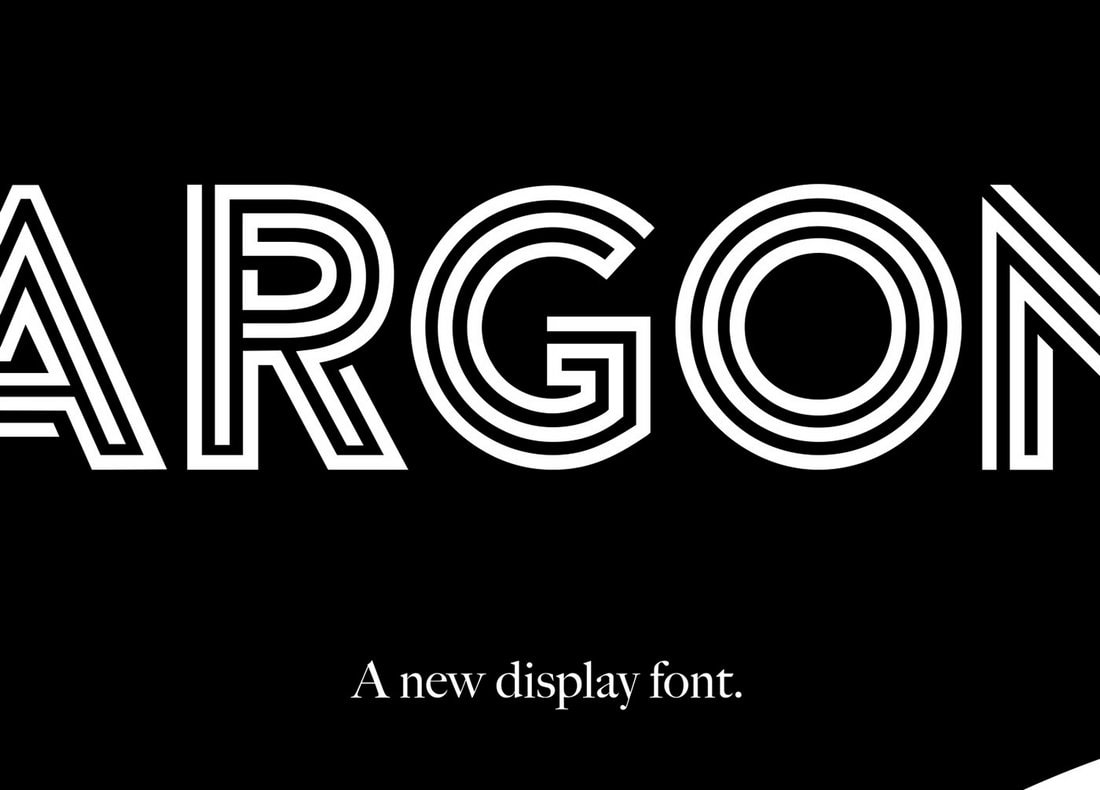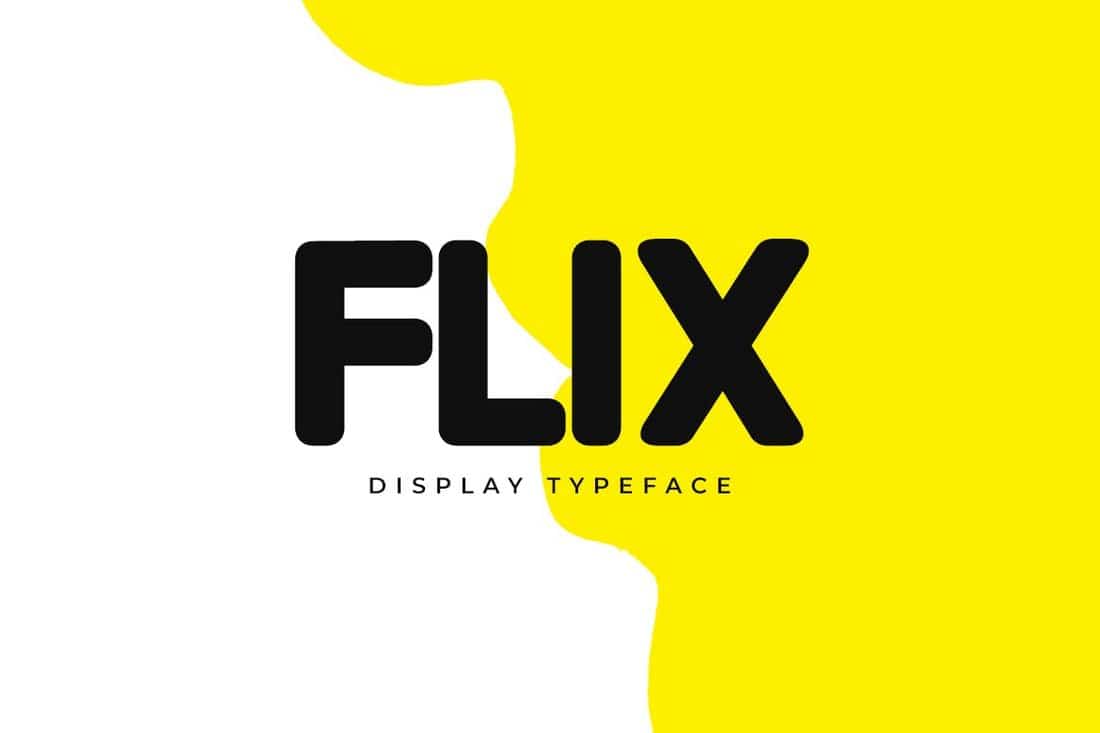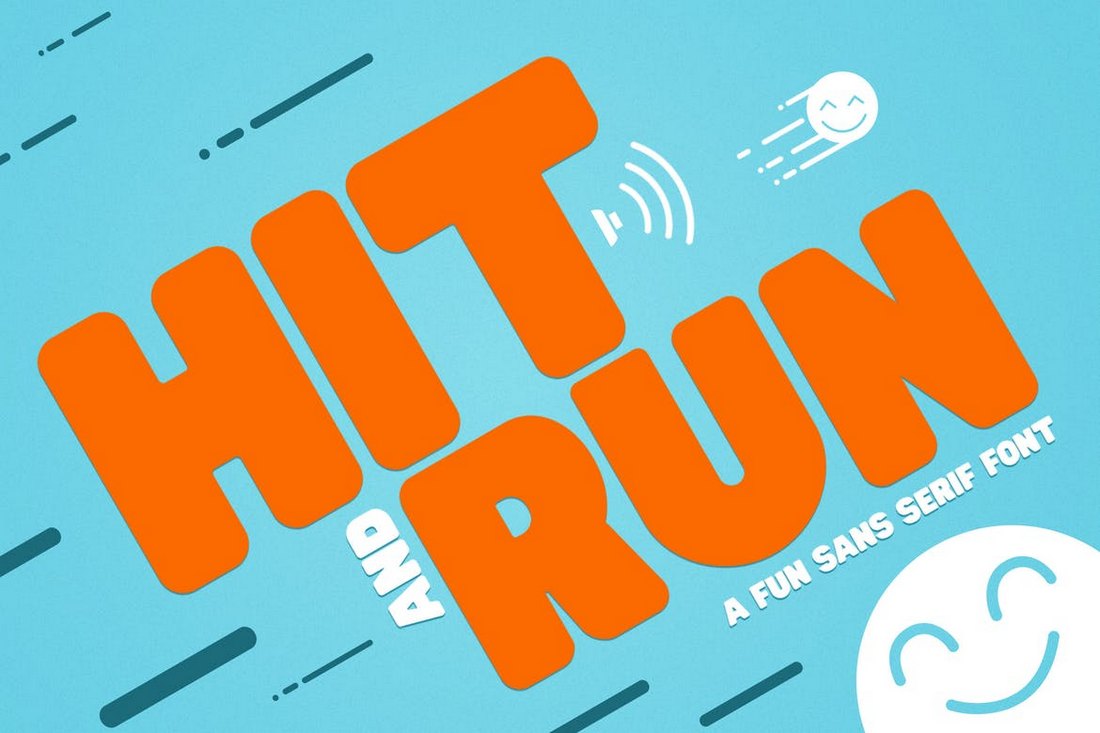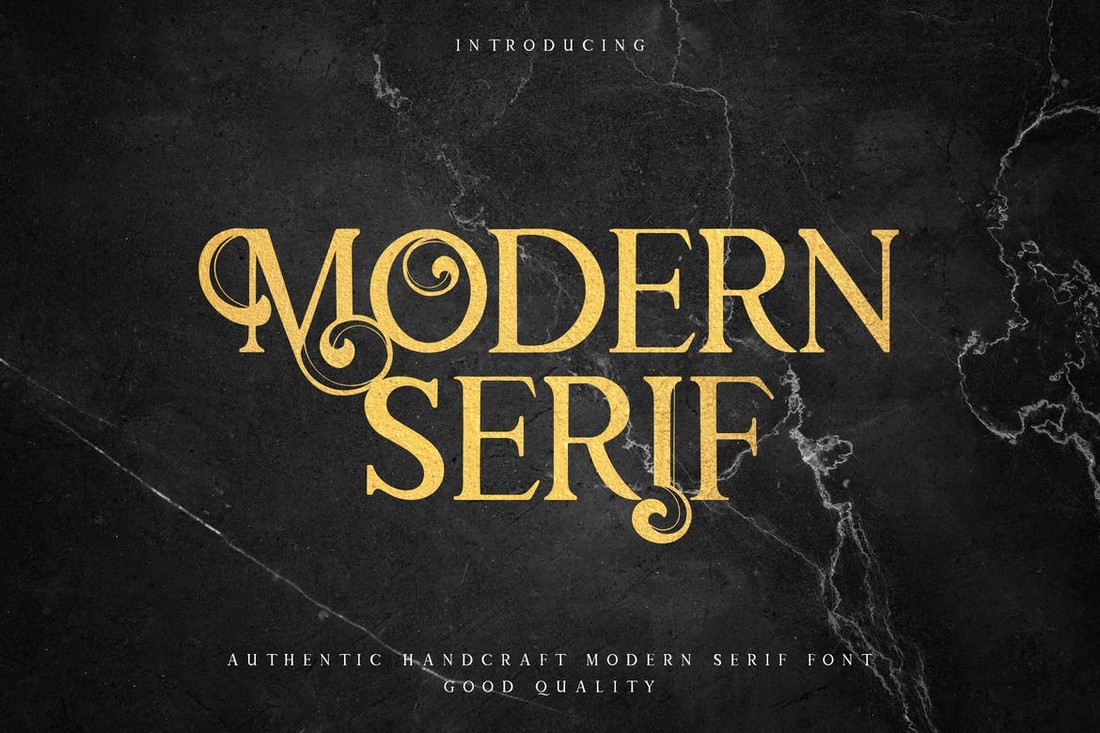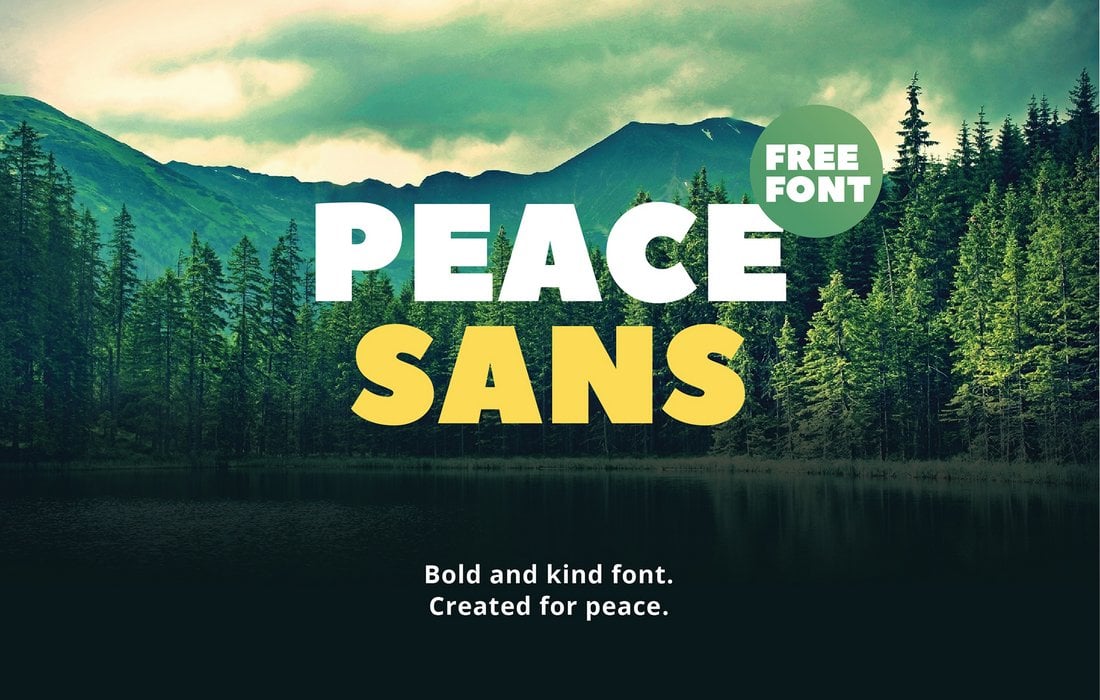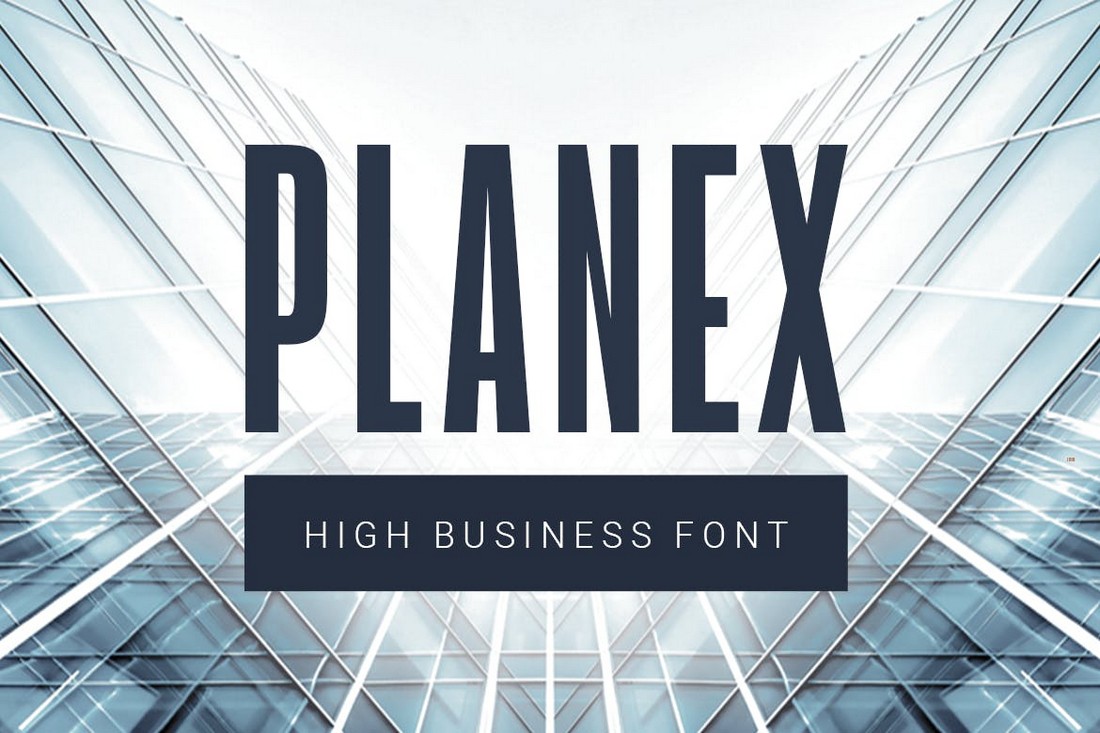
海報和平面項目中最讓人糾結(jié)的一個環(huán)節(jié)也是最重要的一個環(huán)節(jié)就是字體的選擇。 沒有一個合適的,引人注目的標題的海報根本不是有效的海報。
出色的海報字體可以將最簡單的布局變成引人注目的設(shè)計。 正如Irene Etzkorn說過的那樣:“There is no such thing as a boring project. There are only boring executions”。
如果你正在尋找理想的海報字體,或者正在為你的網(wǎng)站設(shè)計等相關(guān)數(shù)字化項目尋找合適的字體,那么相信我們今天的分享將會幫助到你。 我們發(fā)現(xiàn)了一組出色的海報字體,它們非常適合任何類型的海報設(shè)計。 它們足夠大,并且大膽,有創(chuàng)意,足以引起注意!
1.FLIX – Unique Display Font
Flix是一個具有醒目設(shè)計的現(xiàn)代字體。 它具有常規(guī)和輪廓字體樣式,你可以使用它來設(shè)計創(chuàng)意和現(xiàn)代海報的標題。
2.Bright Script – 3-In-1 Big Poster Fonts
Bright是一個會吸引你注意的粗體腳本字體,可用于設(shè)計現(xiàn)代海報,橫幅,網(wǎng)站設(shè)計中的標題等。 該字體有3種不同的樣式,包括簡單,筆刷和分層設(shè)計。
3.Hit and Run – Fun Big Poster Font
Hit and Run是一個有趣的海報字體,其醒目的設(shè)計使其能夠真正脫穎而出。 該字體非常適合用于印刷和數(shù)字設(shè)計,包括網(wǎng)站設(shè)計,社交媒體帖子,海報,賀卡等。
4.Lucita – Stylish Big Poster Font
Lucita是一個時尚而帶有點古怪的海報字體,可用于你的現(xiàn)代和扁平風(fēng)格的設(shè)計項目中。 該字體以O(shè)TF格式提供,并帶有大寫和小寫字母,并包括多語言支持。
5.Forests – Unique Big Poster Font
Forests是一個獨特的分層字體,可用于設(shè)計真正脫穎而出的標題。 字體分為3層,你可以選擇使用3層,2層或單層的字體,還可以根據(jù)自己的喜好自定義顏色。
6.Peace Sans – Free Display Font
Peace Sans是一個大膽的免費字體,你可以用來設(shè)計在眾多作品中脫穎而出的標題樣式。
該字體由專業(yè)人士設(shè)計,具有幾何特征的字符設(shè)計,還提供多語言支持和字形。
7.Argon – Unique Free Poster Font
Argon是一款獨特的海報字體,帶有時尚的輪廓設(shè)計。 該字體非常適合用于制作與奢侈品和時尚有關(guān)的海報設(shè)計。 但是該字體僅能在你的個人項目中免費使用。
8.Modern Mode – Modern Serif Poster Font
這款免費的字體具有現(xiàn)代和復(fù)古元素的混合設(shè)計。 時尚的襯線和優(yōu)雅的設(shè)計使其成為為奢侈品牌和高端企業(yè)制作標題和海報的絕佳選擇。
9.Planex – Business Title Font
Planex是一款設(shè)計大膽的窄風(fēng)格字體,具有簡潔的設(shè)計。 此字體最適合各種專業(yè)和商業(yè)海報設(shè)計以及傳單和網(wǎng)站設(shè)計中的標題設(shè)計。
10.Revoller – Decorative Bold Sans Font
Revoller是一和專門為制作有趣的海報和標題所設(shè)計的字體。 字母的經(jīng)典外觀使該字體成為設(shè)計電影海報和DVD封面的絕佳選擇。
選擇海報字體的3個技巧
如果你還不太了解如何選擇一款合適的字體的話,可以按照以下提示快速查找和匹配適合你的海報設(shè)計的最佳字體。
1.選擇大字體
海報的標題是引起所有人注意的第一件事。 為什么? 因為它是整個海報設(shè)計中最大的文字元素。
海報標題一直以來在字體的選擇上都偏向于大,并且有充分的理由。 那些引人入勝的標題使人們停下來閱讀海報。 因此,在選擇海報字體時,請使用大膽的字體設(shè)計。 更重要的是,以各種海報尺寸打印時,請確??梢哉{(diào)整所使用的字體大小以創(chuàng)建更大的標題,而不會損失其質(zhì)量。
2.選擇合適的字重
字體粗細在海報標題設(shè)計中也起著關(guān)鍵作用。 無論你要使用細體還是粗體,都請記住要充分的考慮海報的實際大小。
例如,如果你正在設(shè)計A4尺寸的海報,則使用較細的字體粗細可能不是理想的選擇,因為當以較小的海報尺寸打印時,很難在遠處被閱讀。
明智地使用字體粗細,并選擇一種具有多種字體粗細的字體,以便你在一開始就有多種選擇。
3.襯線或無襯線字體
擁有窄縮設(shè)計的無襯線字體通常是設(shè)計海報的最佳選擇。 但是,某些類型的海報,例如奢侈品牌的海報,最好使用襯線字體制作。
考慮一下你的品牌形象,目標受眾以及你希望通過海報傳達的總體信息,并選擇一種字體,以突出顯示標題中的所有這些方面。
總結(jié)
這是我們今天分享的一系列美麗而富啟發(fā)性的字體和字體集合。 文章(https://designshack.net/articles/inspiration/best-big-poster-fonts/)中的字體采用粗體,裝飾性腳本以及其他流行的字體設(shè)計元素! 使用這些集合之一為你的下一個設(shè)計項目找到理想的字體。